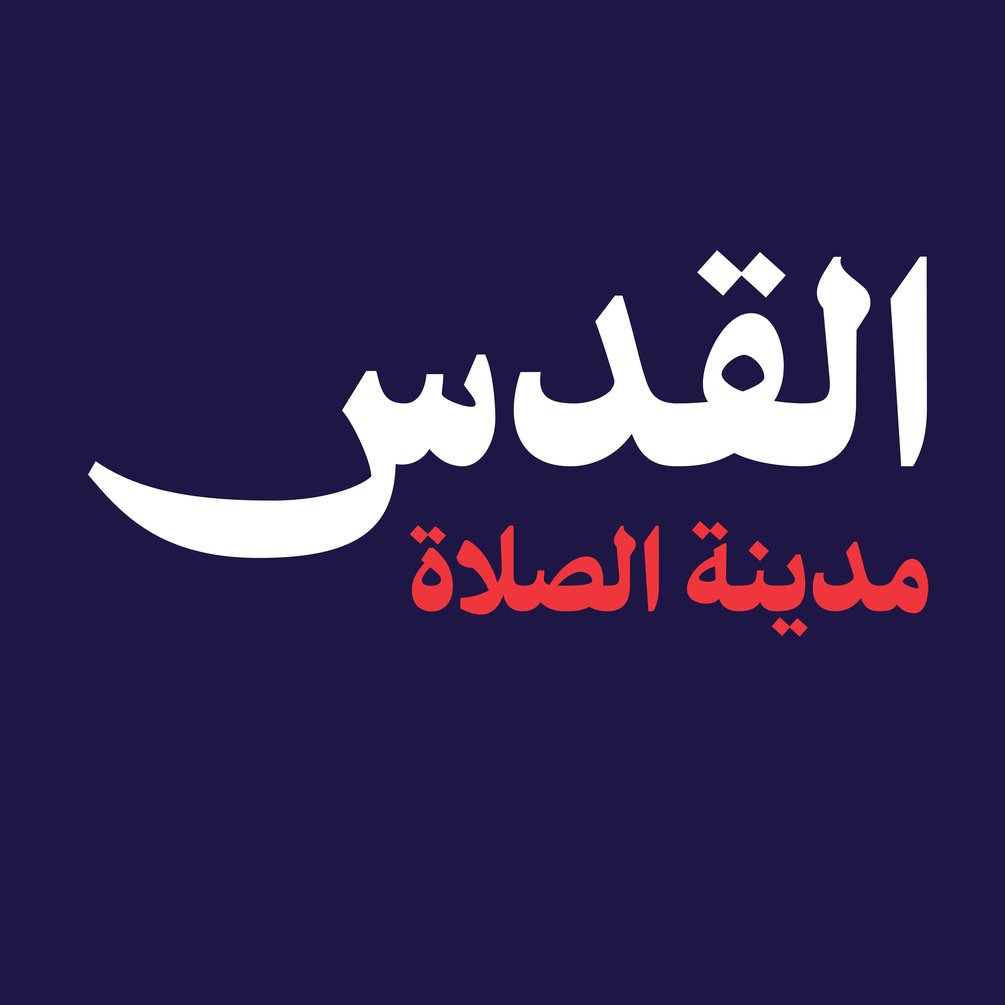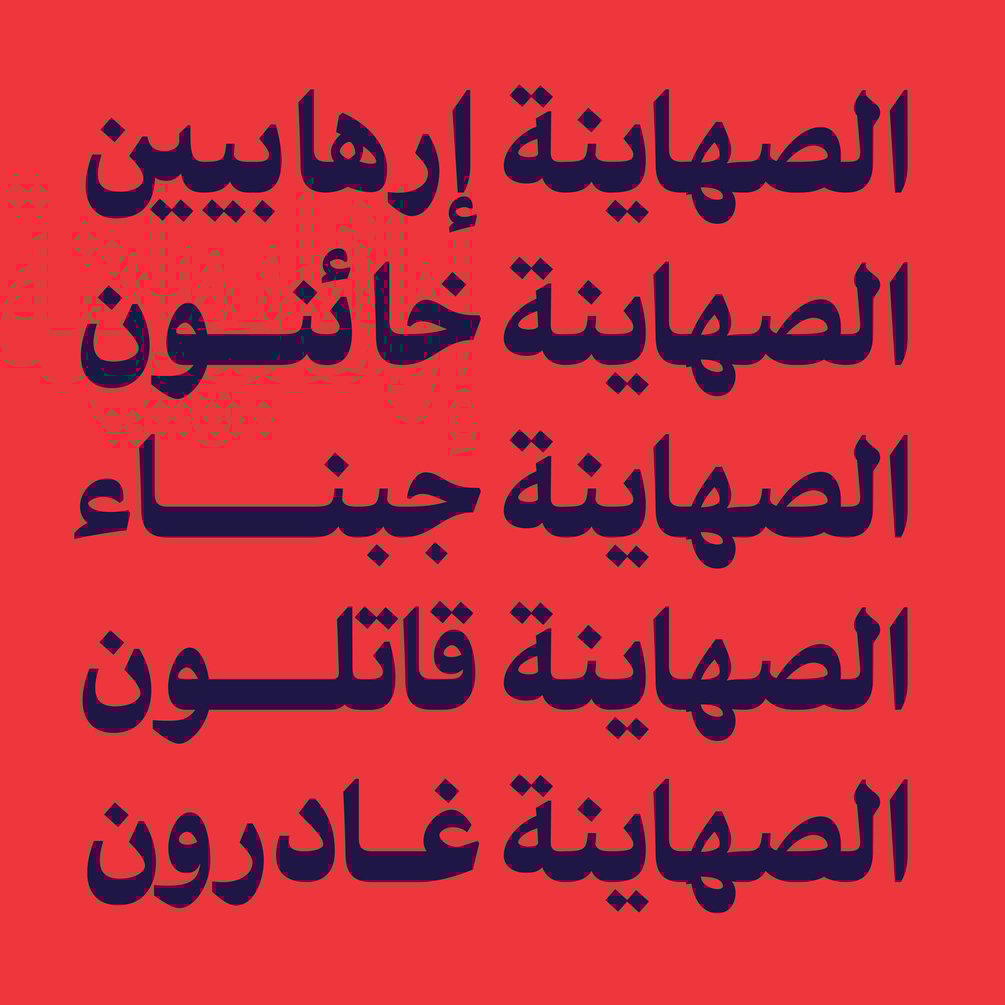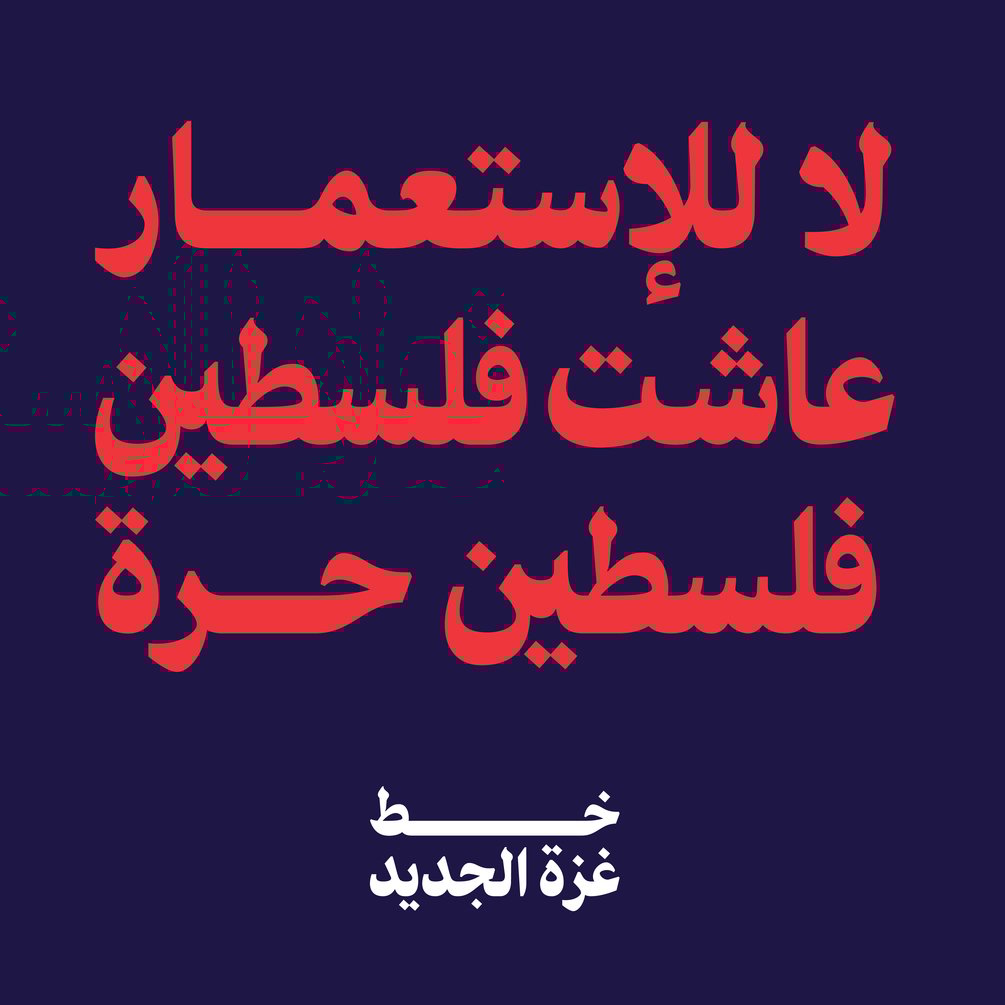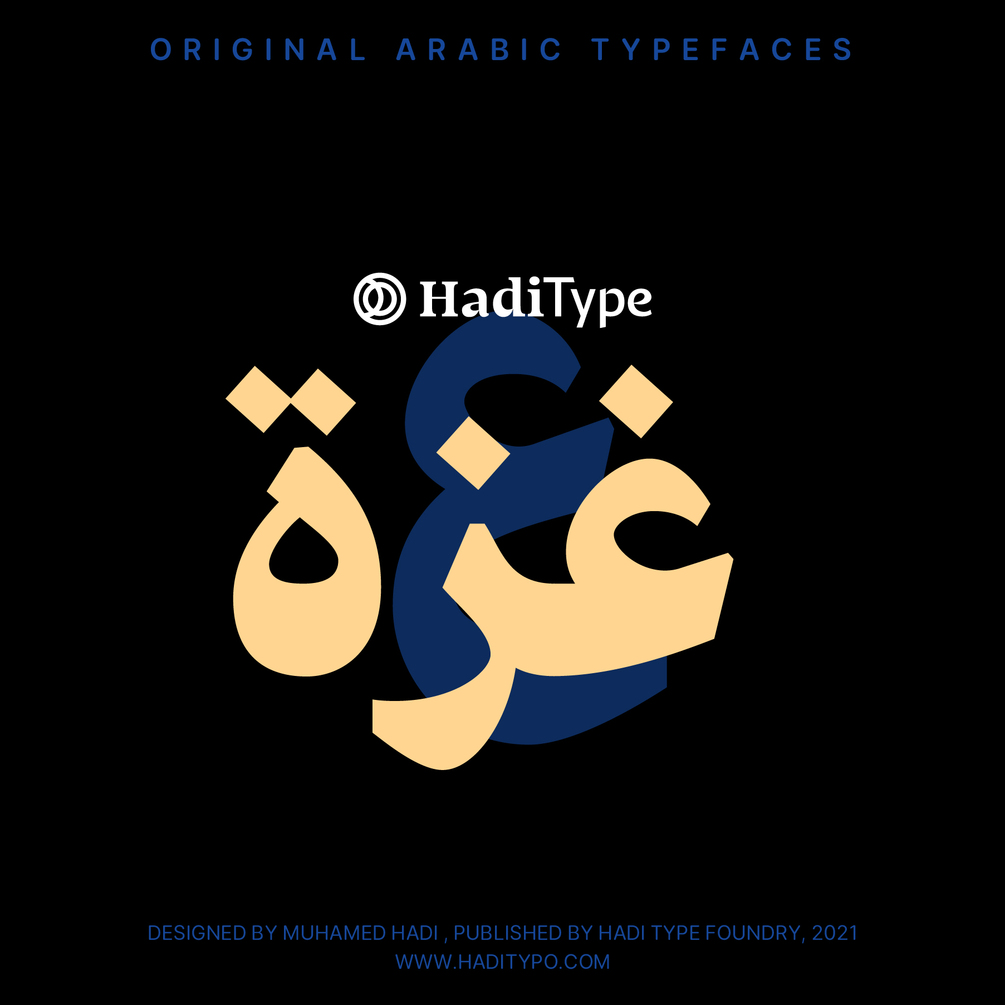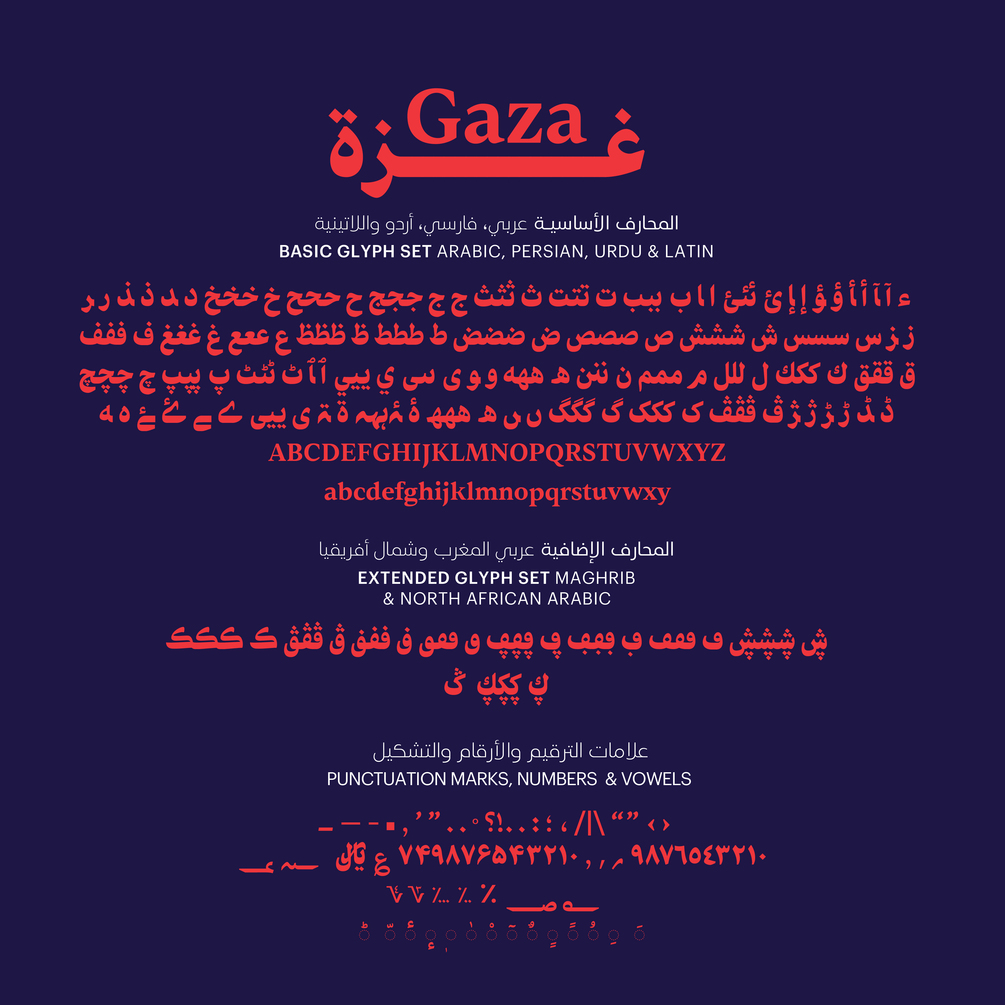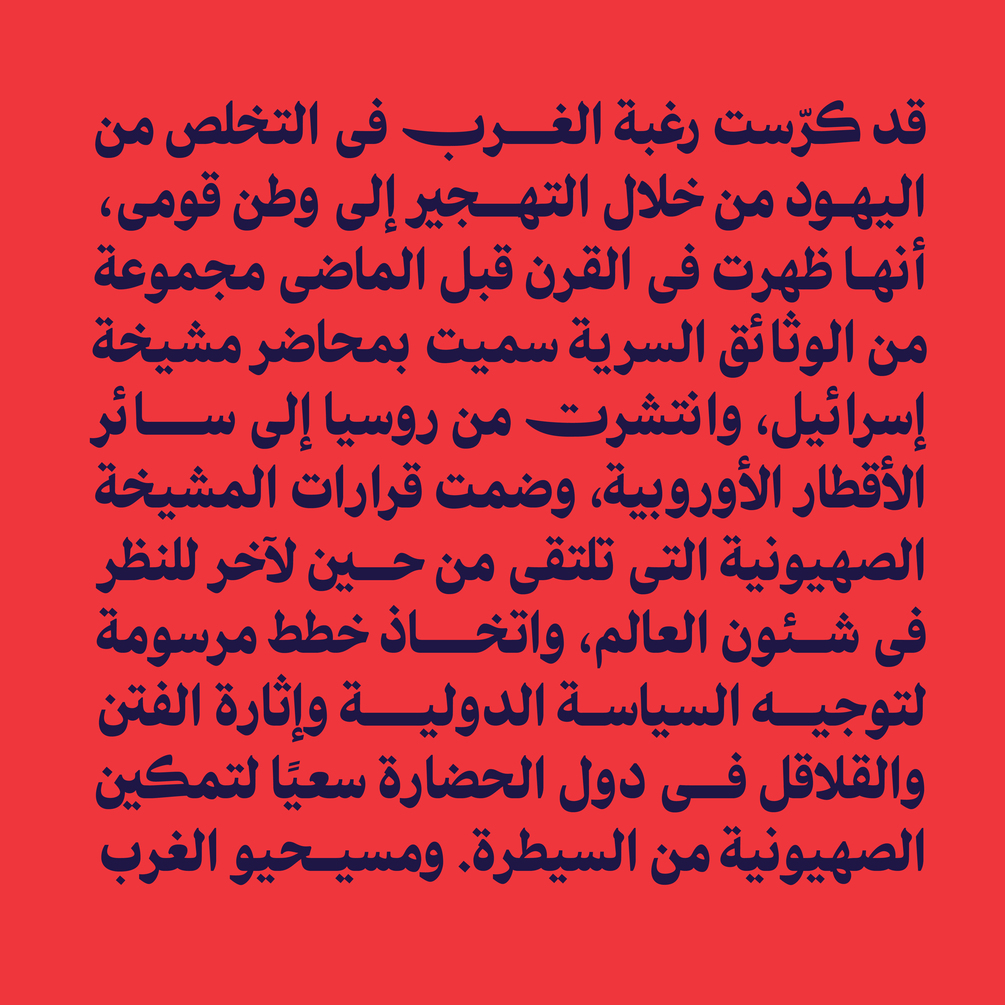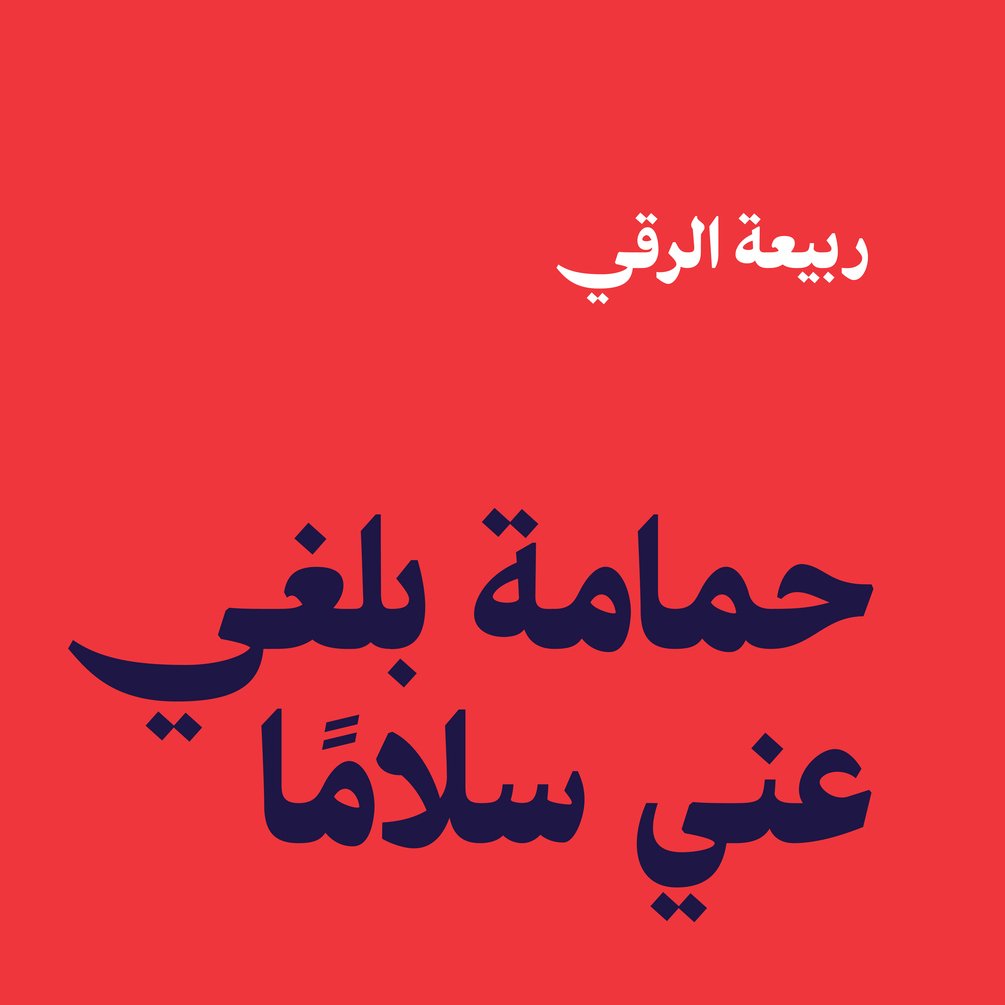
HT Gaza
إصـــــدار جديـــــد.
خط غزة هو خط عربي تقليدي جديد مبني على الأسلوب النسخي، ذو قاعدة عريضة يصلح لأعمال العناوين والمنشيتات الصحفية، وهو مبادرة من شركة حروف هادي لدعم متضرري غزة وستؤول كامل ارباحه دعمًا لهذا الشعب الصامد، الخط يتكون من وزن واحد فقط.
يحتوي الخط على اللغة العربية والفارسية والاردية وعربي المغرب وشمال افريقيا واللاتينية وبه مجموعة متنوعة من تبديلات الحروف والحروف الممدوة،
New Release.
Gaza font is a traditional-style Arabic display typeface. its design is ultra bold, its forms remain a readable Naskh, in response to the needs of secular lettering for emphatic headlines and signs. Gaza font characterized by a distinctive, strong baseline-stroke, reminiscent of a similar hand-rendered technique traditionally used in Arabic calligraphy to achieve a bold appearance.
Gaza font Supports Arabic, Persian, Urdu, Maghrib & North Africa Arabic, it includes tabular Arabic and Persian numerals.